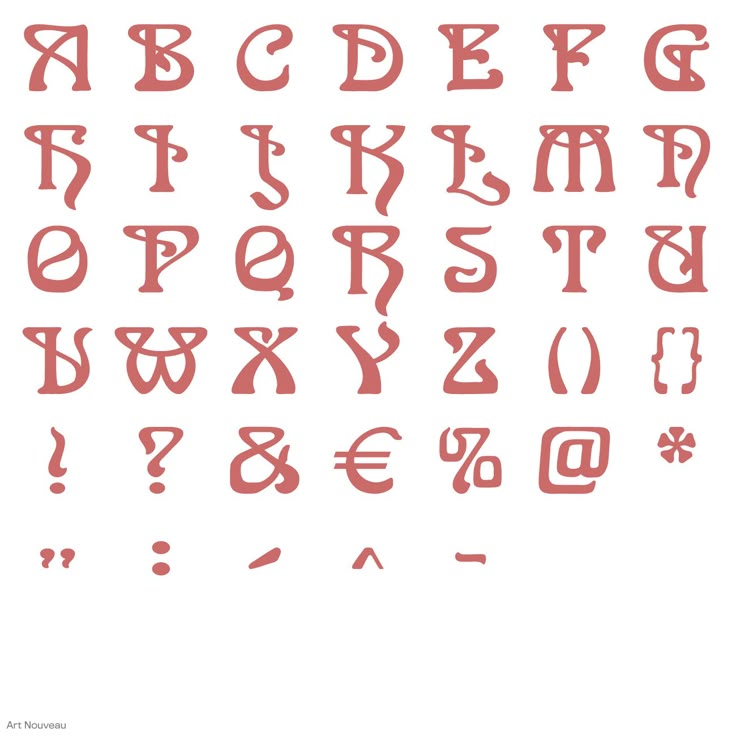
Элегантные шрифты ар-нуво
Ар-нуво, или модерн, как его называют в России — это художественное направление в искусстве, архитектуре и дизайне шрифтов.
Шрифты в коллекции содержат полный набор западноевропейских диакритических символов и знак евро. Более того, многие шрифты также включают в себя восточноевропейские, балтийские и турецкие символы.
«И дольше века длится…»
«Купола в России кроют чистым золотом, чтобы…» (вместо предисловия)
Ар нуво — «наше» и «не наше»
Ар нуво — многоликий стиль: почти эталонный, почти привычный…
«Купола в России кроют чистым золотом, чтобы…» (вместо предисловия)
Почти двадцать лет тому назад (то есть еще при Советской власти) автора этой публикации удивили и даже поразили несколько графических образов (рис.
1). Одним из первых впечатлений в этом ряду стала открыточная репродукция, на которой был изображен храм Святого Семейства в Барселоне (архитектор А.Гауди). Другие примеры, возможно, были несколько менее впечатляющими, но вместе с тем они ощутимо расходились с теми образами, которые были характерны для социалистического реализма. Приведенные на рисунке образцы по большей части достаточно хорошо известны и принадлежат к значимым памятникам раннего модерна, который в западных источниках до сих пор чаще всего именуют Art Nouveau. Кстати, условимся, что в дальнейшем мы будем использовать этот термин в его вполне устоявшемся транскрибированном звучании — ар нуво (в буквальном переводе данное словосочетание означает «новое искусство»). Отметим, что уже в 90-х в нашем отечестве, к счастью, была практически изжита традиция прежних лет, когда даже в специальных изданиях можно было столкнуться с полностью синонимическим употреблением терминов «ар нуво» и «модерн».
Рис.
1
Ар нуво оказало поистине революционное воздействие на всё декоративноприкладное искусство XX века, став источником многих основополагающих идей, развиваемых и поныне. Достаточно, например, напомнить, что и Art Deco, и функционализм находятся в прямой преемственности с этой эстетикой, а такие оказавшие неизгладимое влияние на графику прошлого века культовые центры, как, например, Сецессион и Баухауз, вполне могут быть уподоблены побегам, произросшим в этой новаторской эстетике.
Однако стоит вернуться к приведенному комбинированному примеру и хотя бы кратко его прокомментировать. На центральном фрагменте приведено изображение вышеупомянутого собора, который, будучи еще не завершенным в строительстве, попал в золотой фонд архитектурных памятников человечества. В левой части рисунка представлен фрагмент театрального плаката чешского художника и дизайнера А.Мухи, а справа — фрагмент календаря этого же автора. Текстовые фрагменты нижней части календаря в малом формате практически невоспроизводимы, а по этому попали в обрез, однако в самом верху даже без увеличительного стекла можно прочесть девизный акцидентный текст «La Plume», выполненный рукой этого признанного мастера.
Фрагменты работ А.Мухи являются яркими примерами типографических образцов, использовавшихся во время становления модернистской эстетики, когда только зачиналась акцидентная типографика ар нуво.